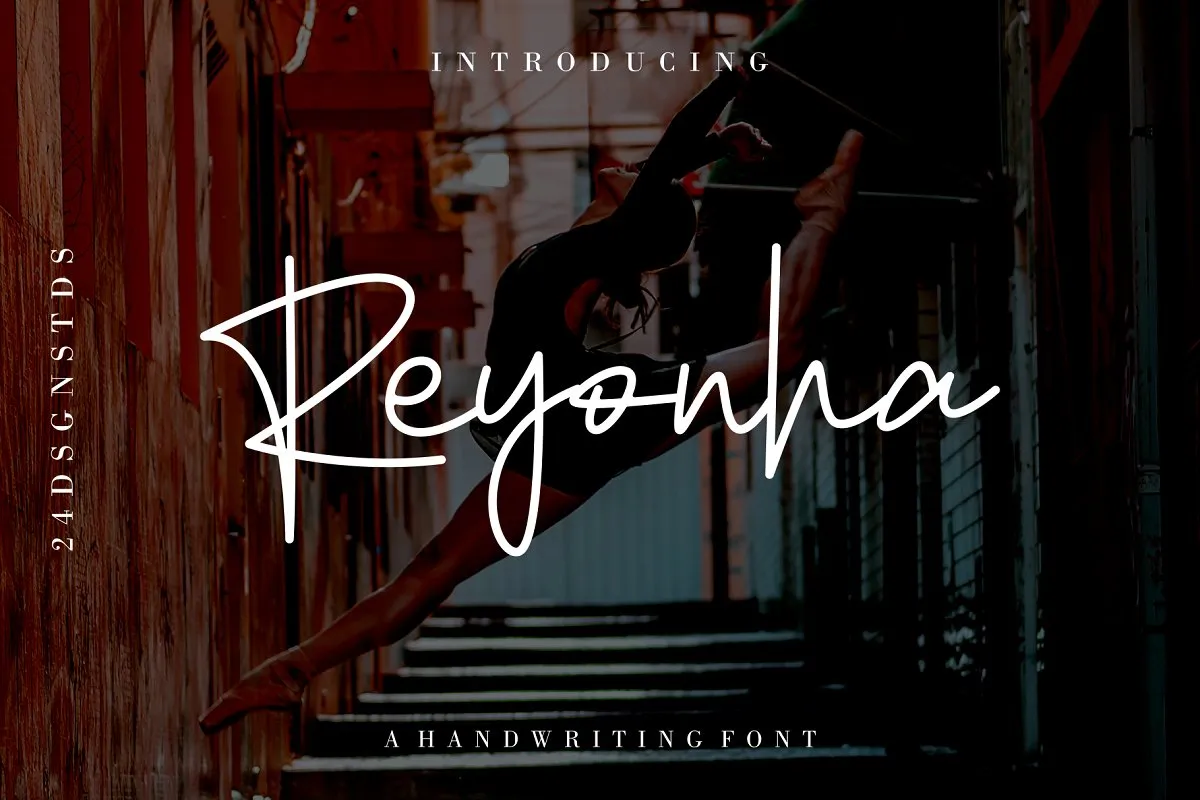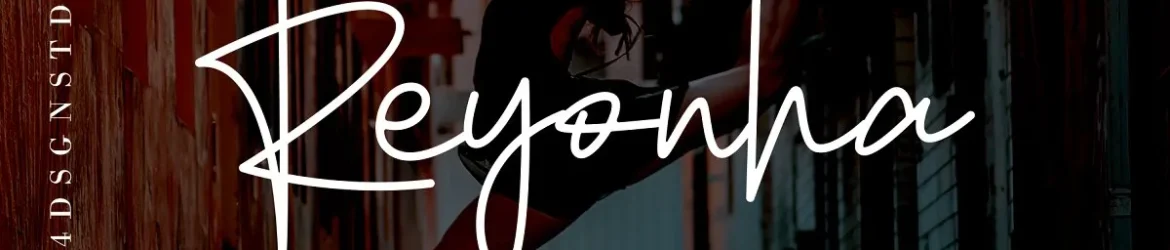
Reyonha Handwriting Font – Download Grátis
Estamos honrados por você escolher a fonte Reyonha Handwriting Font na categoria de fonts Script. Esta font foi projetada para atender a uma ampla gama de necessidades, desde design de logotipos até criação de livros e editoriais femininos. Desenhada pela 24Design Studios, esta font é perfeita para aqueles que buscam um toque moderno na sua produção visual. Reyonha Handwriting Font tem uma aparência simples, mas transmite o encanto moderno através do seu estilo de escrita manuscrita única. Suas linhas monolineares tornam-a ideal para títulos e edições que exigem delicadeza ou romantismo feminino. A fonte atende perfeitamente a necessidade de incorporar uma pegada romântica na sua marca, seja em um editorial de moda, livro de receitas ou logotipos exclusivos. Escolha Reyonha para dar ao seu projeto um toque único e moderno, que captura o espírito feminino tão característico. Com certeza, ela não é apenas uma font, mas uma escolha cuidadosa em se tornar parte integral de qualquer obra visual.